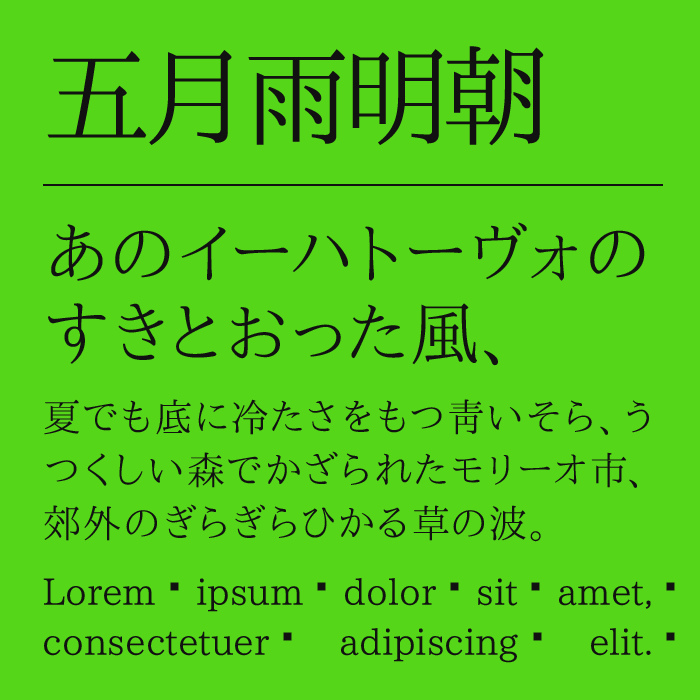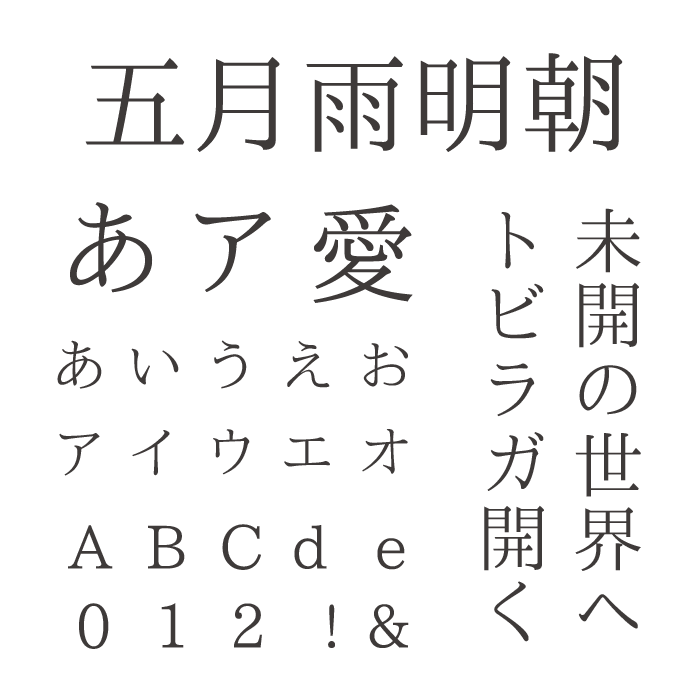
五月雨明朝
五月雨明朝フォントは、細く繊細な線で構成された、美しく静かな印象の明朝体フォントです。
余白を活かした軽やかなデザインが特徴で、雨音が静かに響くような落ち着いた空気感があります。シャープさの中にもやわらかさがあり、文字を並べるだけで上品で透明感のある世界観を演出できるフォントです。
文学作品や和風デザイン、詩的なビジュアルなどと相性が良く、静かな感情を丁寧に引き立ててくれます。長文でも圧迫感が少なく、読み進めるほどに余韻が広がっていくような魅力があります。控えめでありながら深い存在感を持つ、美しい明朝体フォントです。
五月雨明朝
収録文字は、漢字・ひらがな・カタカナ・アルファベット・数字・記号が収録。